타이포그래피 기초를 처음부터 체계적으로 익히는 방법
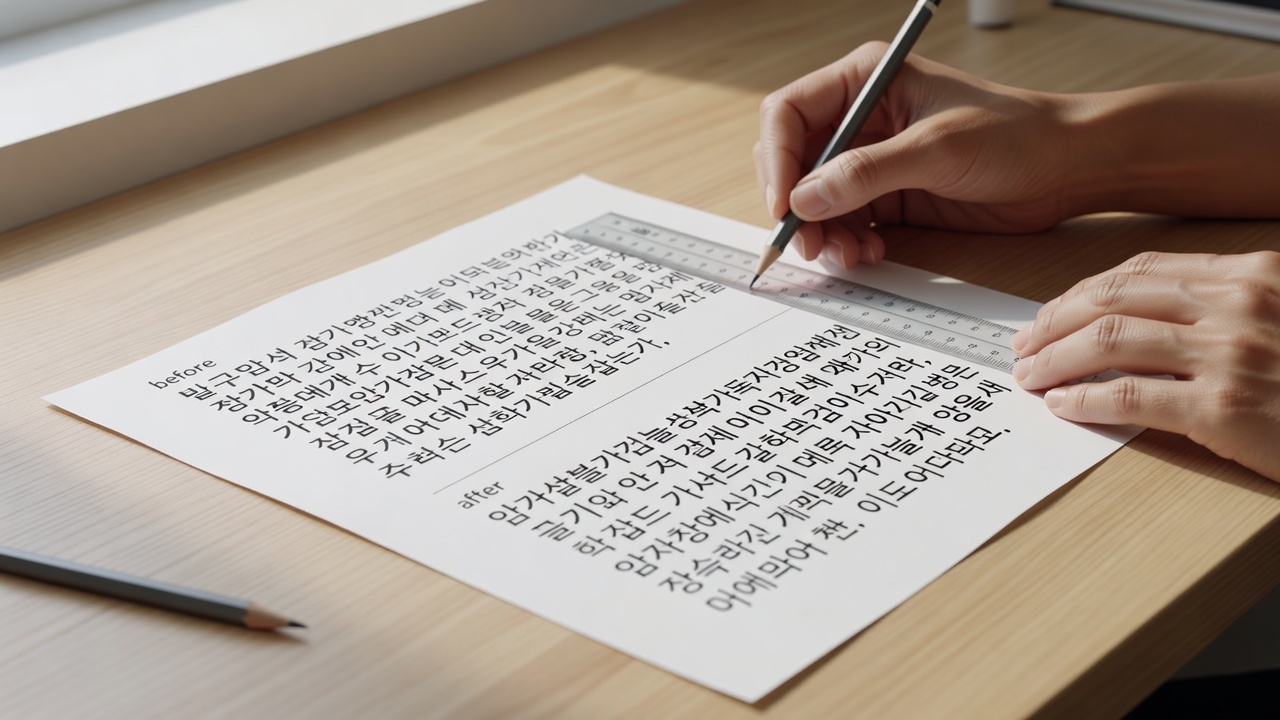
타이포그래피 기초는 글꼴·크기·간격·대비의 네 가지 원칙을 순서대로 배우는 것이 가장 효과적입니다. 이 순서를 따라 학습하면 초보자도 체계적으로 디자인 감각을 키울 수 있으며, 이후 한글과 영문 모두에 적용 가능한 기반이 됩니다. 2026년 현재에도 대부분의 타이포그래피 교육 과정이 이 네 가지 원칙을 중심으로 구성되어 있습니다.
타이포그래피 기초 원칙 이해하기
타이포그래피 기초를 처음 접하는 사람은 네 가지 원칙을 순서대로 익히는 것이 가장 안정적입니다. 글꼴을 먼저 이해한 뒤 크기, 간격, 대비 순으로 접근하면 논리적 흐름이 생깁니다.
각 원칙은 독립적이지 않고 서로 영향을 주고받습니다. 예를 들어 글꼴을 잘못 선택하면 이후 크기와 간격 조정이 어려워집니다. 따라서 첫 단계에서 글꼴의 기본 특성을 파악하는 연습이 필요합니다.
글꼴의 특성과 선택 기준
글꼴은 세리프와 산세리프, 고딕과 명조 등 큰 카테고리로 나뉩니다. 2026년 현재도 한글 디자인에서는 산세리프 계열이 본문용으로 많이 사용되며, 세리프는 제목이나 강조에 적합합니다.
선택 기준은 용도와 분위기입니다. 본문은 가독성이 높은 글꼴을, 제목은 개성을 드러내는 글꼴을 고르는 것이 일반적입니다. 여러 글꼴을 섞을 때는 계열이 다른 두 가지 이상을 동시에 쓰지 않는 것이 안전합니다.
텍스트 크기와 계층 구조 설계
크기는 단순히 숫자가 아니라 시각적 계층을 만드는 도구입니다. 제목, 부제, 본문, 캡션 순으로 크기를 단계적으로 줄이면 독자가 자연스럽게 정보를 따라갑니다.
크기 차이가 너무 작으면 계층이 약해지고, 너무 크면 페이지가 산만해집니다.
자간·행간 조정으로 리듬 만들기
자간과 행간은 글의 리듬을 결정합니다. 한글은 자소가 복잡하기 때문에 영문보다 약간 넓은 자간이 읽기 편합니다. 행간은 글꼴 크기의 1.5–1.8배를 기본으로 삼는 것이 무난합니다.
너무 좁은 간격은 글자가 붙어 보이고, 너무 넓으면 내용이 끊어져 보입니다. 실제 작업에서는 0.1단위로 미세 조정하며 테스트하는 과정이 필요합니다.
색상 대비와 가독성 확보
대비는 텍스트와 배경 사이의 명도 차이를 의미합니다. WCAG 기준에 따르면 본문 텍스트는 최소 4.5:1 이상의 대비율을 유지하는 것이 권장됩니다.
어두운 배경에 밝은 글자를 쓸 때는 대비를 더 높여야 합니다. 색상만으로 대비를 주려다 보면 접근성 문제가 발생할 수 있으므로, 명도 차이를 먼저 확인하는 습관이 중요합니다.
한글 타이포그래피 적용 사례
한글은 초성·중성·종성이 결합되는 구조 때문에 영문보다 복잡한 공간감을 갖습니다. 최근 브랜딩 프로젝트에서는 산세리프 글꼴에 적절한 자간을 더해 깔끔한 인상을 주는 경우가 많습니다.
실제 사례를 분석할 때는 단순히 예쁜 결과물만 보지 말고, 크기와 간격 수치를 함께 기록해 두는 것이 학습에 도움이 됩니다. 이를 통해 자신의 작업에 바로 적용할 수 있는 구체적인 기준이 생깁니다.
실전에서 자주 하는 실수와 해결
초보자가 가장 많이 하는 실수는 여러 글꼴을 무작정 섞는 것입니다. 두세 가지 이상의 글꼴을 동시에 사용하면 통일감이 떨어집니다.
또 다른 실수는 행간을 너무 좁게 잡는 것입니다. 특히 모바일 환경에서는 1.6배 이상의 행간이 필수적입니다. 미리 여러 디바이스에서 미리보기를 해보는 습관을 들이면 이런 문제를 줄일 수 있습니다.
타이포그래피 기초를 배우는 데 얼마나 걸리나요?
개인차가 있지만 매일 1시간씩 실습하면 4–6주 정도면 네 가지 원칙을 기본적으로 다룰 수 있습니다. 이후 실제 프로젝트에 적용하며 감각을 다지는 기간이 추가로 필요합니다.
한글과 영문 타이포그래피는 동시에 배워도 되나요?
기본 원칙은 동일하므로 동시에 배워도 됩니다. 다만 한글의 자소 구조를 먼저 이해한 뒤 영문에 적용하는 순서가 혼란을 줄이는 데 효과적입니다.
무료 글꼴만으로도 충분한가요?
기초 학습 단계에서는 무료 글꼴만으로도 충분합니다. 상업 프로젝트를 진행할 때가 되어서야 유료 글꼴의 필요성을 느끼는 경우가 일반적입니다.
자간과 행간은 어떤 기준으로 조정하나요?
글꼴 크기의 1.5–1.8배 행간과 0.02–0.05em 정도의 자간을 기본값으로 시작해, 실제 텍스트를 읽으면서 미세 조정하는 것이 가장 정확합니다.
모바일과 데스크톱에서 동시에 고려해야 하나요?
반응형 디자인을 고려한다면 두 환경 모두에서 테스트해야 합니다. 특히 모바일에서는 행간을 더 넓게 잡는 것이 가독성에 유리합니다.
결론